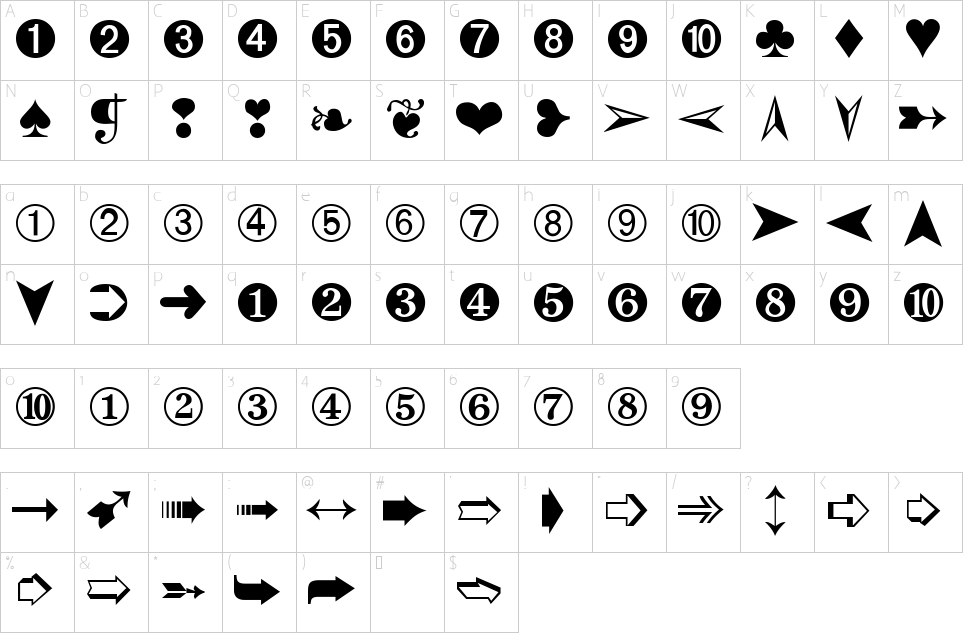
A Digits Font é uma opção perfeita para quem busca uma fonte moderna e funcional para projetos digitais. Desenvolvida pelo talentoso designer Dieter Steffmann, a Digits foi criada com uma linguagem clean e minimalista que se adequa bem a texturas de websites ou aplicativos de interface simples. Essa fonte foi projetada especificamente para oferecer um equilíbrio perfeito entre legibilidade e estética, tornando-a ideal tanto para títulos quanto para o corpo do texto. Se você está procurando uma opção gratuita para seu projeto em Windows ou Mac, a Digits é sem dúvida uma ótima escolha. Com mais de 35.000 downloads, sabemos que sua simplicidade e praticidade fazem dela uma fonte popular entre designers profissionais.